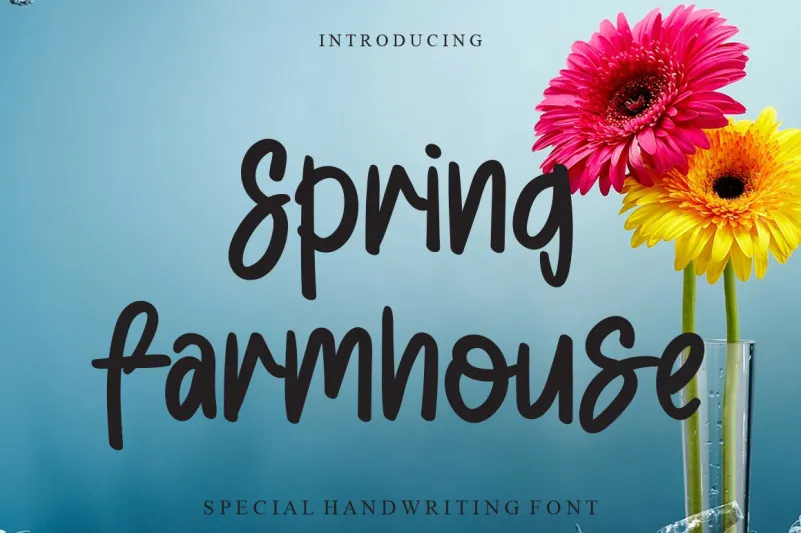
Spring Farmhouse Font – Download Grátis
Essa é uma fonte autêntica e curvilínea, elaborada manualmente com delicadeza. É perfeita para designers que desejam adicionar um toque de descontração a seus projetos gráficos. Com seu ar suave e delicado, essa fonte dará vida às suas criações, trazendo uma atmosfera leve e romântica ao design de cada projeto. É ideal para trabalhos que buscam transmitir um sentimento alegre e romântico. Ideal para aplicação em nomes e títulos, esse fonte oferece um toque cuidadosamente feito à sua marca ou produto.